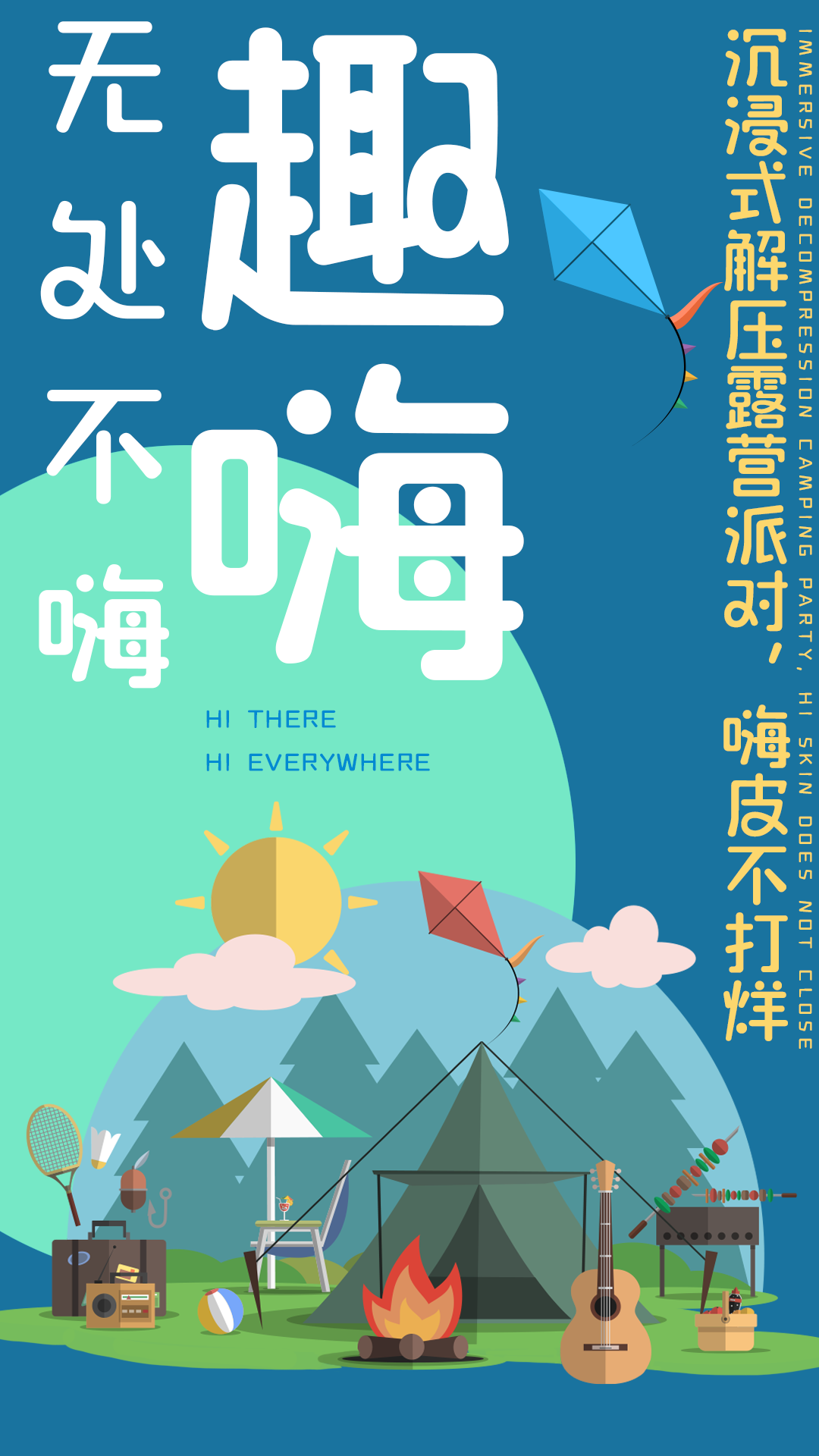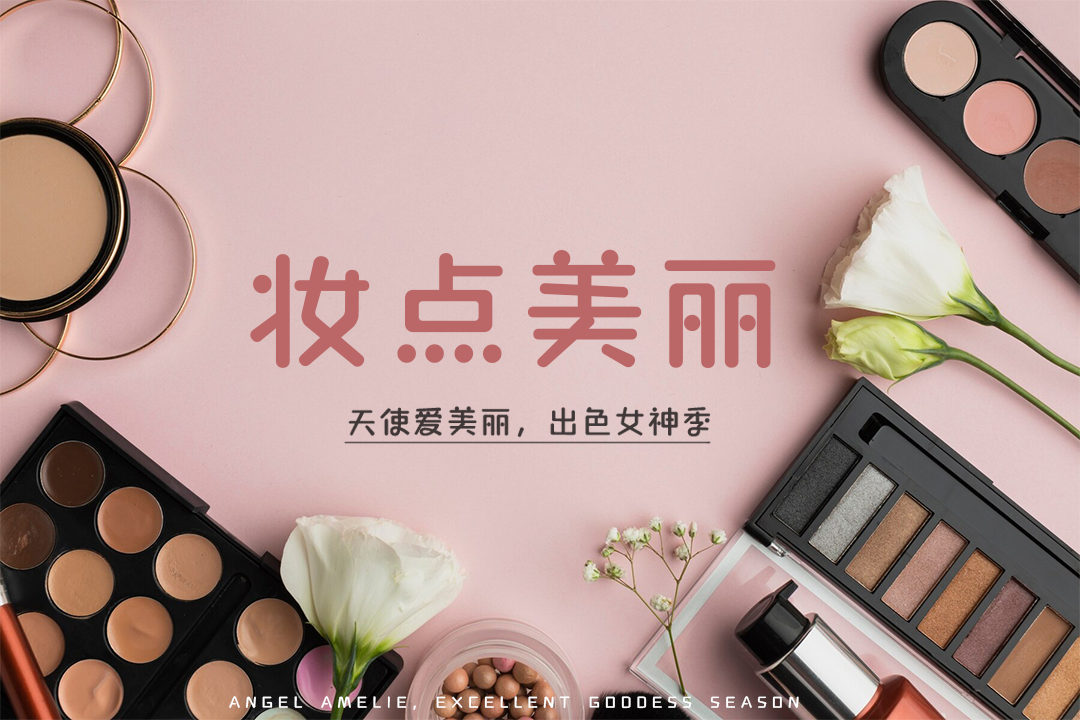
露营是成年人的解压药,偶尔跟生活请个假,呆在没有天花板的地方,夜晚来临时打开星星灯,听听青蛙与蟋蟀的吵闹,收获自然里的无限浪漫。
海派腔调森系圆,一款圆润俏皮的圆体字,灵动活泼的圆点笔画,流畅柔和的连笔设计,仿佛徜徉在自然森林的鲜氧里。生活无解,自然撒野,摁下Start键,跟随森系圆开启一场城市出逃计划。
圆是一种态度,是与生活短兵相接的缓冲面。森系圆将部分笔画锋利的锐角替换成圆弧,点捺部分用可爱俏皮的圆点代替,使视觉效果更具现代美感与弹性。
笔画的排列创造巧妙的平衡,清新活泼的字体形态,松散的中宫结构,使森系圆拥有舒展的留白空间,同时筋骨灵动自然,极赋韵律感与呼吸感。
笔画链接部分采用连笔方式,融合了手写的简洁流畅感,弧度的处理更加柔和,极好的平衡了繁琐的笔画链接方式,凸显点线交互的趣味几何性设计。
让忙碌的生活慢下来,去大自然给心灵冲冲电。俏皮可爱的海派腔调森系圆,可应用于旅行、短视频、海报、LOGO、广告等多种趣味场景,激发多元设计灵感。